Mỗi dịp Trung Thu đến, nhu cầu thiết kế poster, banner, bao bì hộp bánh hay thiệp mời lại tăng cao. Một yếu tố quan trọng tạo nên thành công của thiết kế chính là font chữ. Những font chữ mang phong cách Trung Thu, cổ trang, retro hoặc thư pháp không chỉ giúp sản phẩm ấn tượng hơn mà còn tái hiện rõ nét không khí lễ hội đoàn viên.
Trong bài viết này, S99.vn tổng hợp 28 font chữ Trung Thu & cổ trang Việt hóa 2025, được chọn lọc kỹ lưỡng, đầy đủ dấu tiếng Việt và dễ dàng ứng dụng trong in ấn, truyền thông. Đây là bộ sưu tập hữu ích cho designer, marketer và những ai yêu thích sáng tạo.
Font chữ là yếu tố quan trọng giúp tái hiện không khí Trung Thu trong thiết kế. Việc chọn đúng font tạo nên sự khác biệt, giúp ấn phẩm nổi bật và dễ ghi nhớ.
Không chỉ mang tính thẩm mỹ, font Trung Thu còn khơi gợi cảm xúc: thư pháp trang trọng, retro hoài niệm, nghệ thuật và viết tay thì gần gũi, sáng tạo.
Đặc biệt, nhờ được Việt hóa đầy đủ dấu, các font này dễ dàng ứng dụng trong in ấn và digital marketing, phù hợp cho poster, thiệp mời hay bao bì hộp bánh.
Font Thư Pháp: FZ Đức Thủy, FZ Đại Tự, FZ Tiểu Tự, UTM Thiên Ân, FZ Bút Bi.
Font Cổ Trang: LNTH Peterobscure, Chinese Prodigy, MTD Briliants, NVN Morning Calm, TH Hidayatullah.
Font Hoài Cổ: SVN Moshimoshi, TH Hoaico 1, TH Hoaico 2, DT Phudu, TH Culture.
Font Retro & Bao Cấp: TH Gibsons One, Stampa, MJ Milestone, MJ Caster, TH Hoài Cổ 2.
Font Lịch Sử & Trung Hoa: TH Nhật Bản 1, TH Lịch Sử 1, TH Lịch Sử 3, TH China 1.
Font Viết Tay & Nghệ Thuật: TLM KZ Bladerunner, FZ Christmas Carol, TH Hildesheim.
Dưới đây là danh sách 28 font chữ đa dạng từ thư pháp, cổ trang, retro đến nghệ thuật. Tất cả font đều hỗ trợ đầy đủ tiếng Việt, dễ sử dụng cho in ấn và thiết kế digital, giúp bạn tạo nên ấn phẩm Trung Thu ấn tượng và đậm chất văn hóa.
FZ Đức Thủy mang phong cách thư pháp Á Đông với nét bút uyển chuyển, mềm mại nhưng dứt khoát. Font lý tưởng cho thiệp mời, câu đối, backdrop Trung Thu hay Tết cổ truyền. Nó vừa giữ được tính nghệ thuật vừa đảm bảo độ dễ đọc.
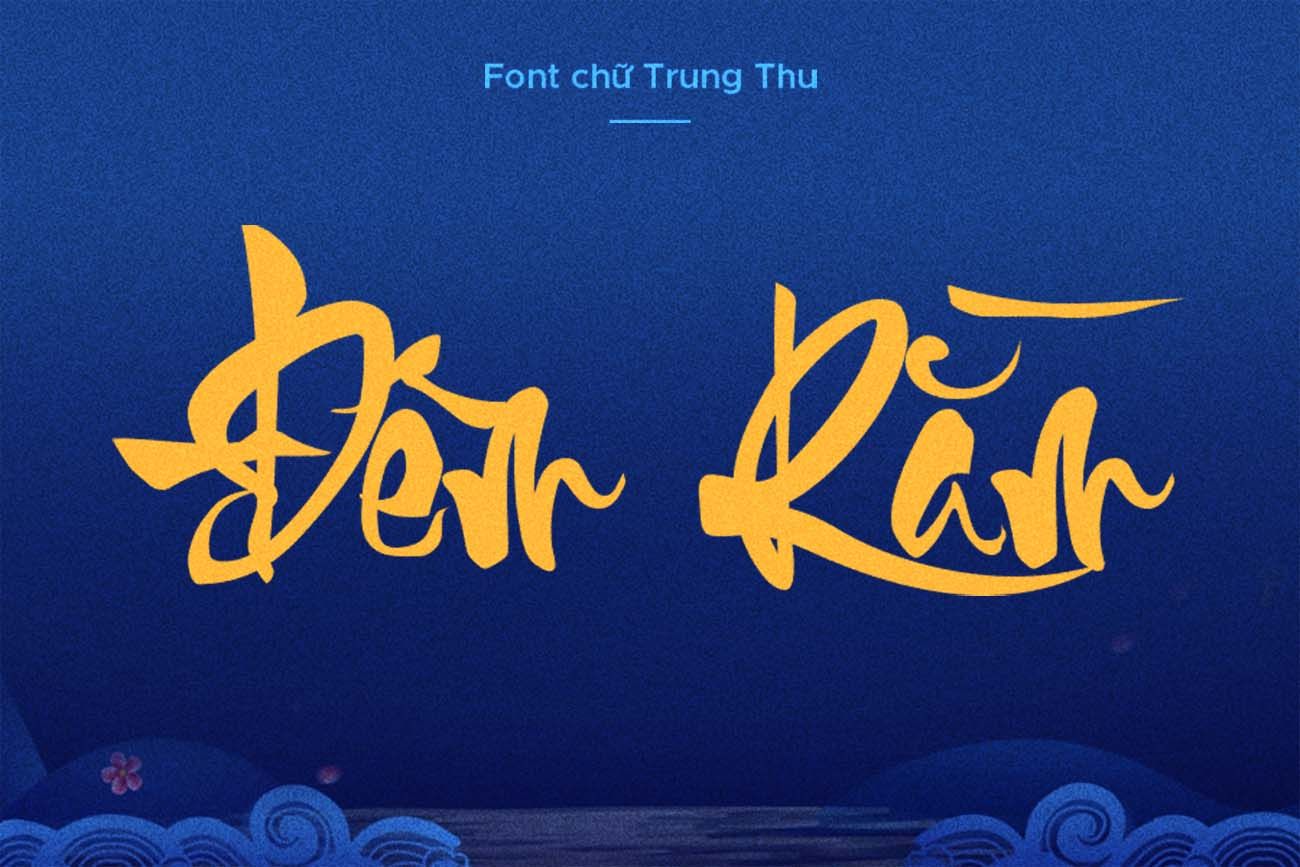
FZ Đại Tự gây ấn tượng với nét bút dày, khoáng đạt. Font này phù hợp cho standee, backdrop sự kiện hoặc bao bì hộp bánh cao cấp. Sự cổ kính và sang trọng của Đại Tự khiến nó nổi bật trong các thiết kế truyền thống.
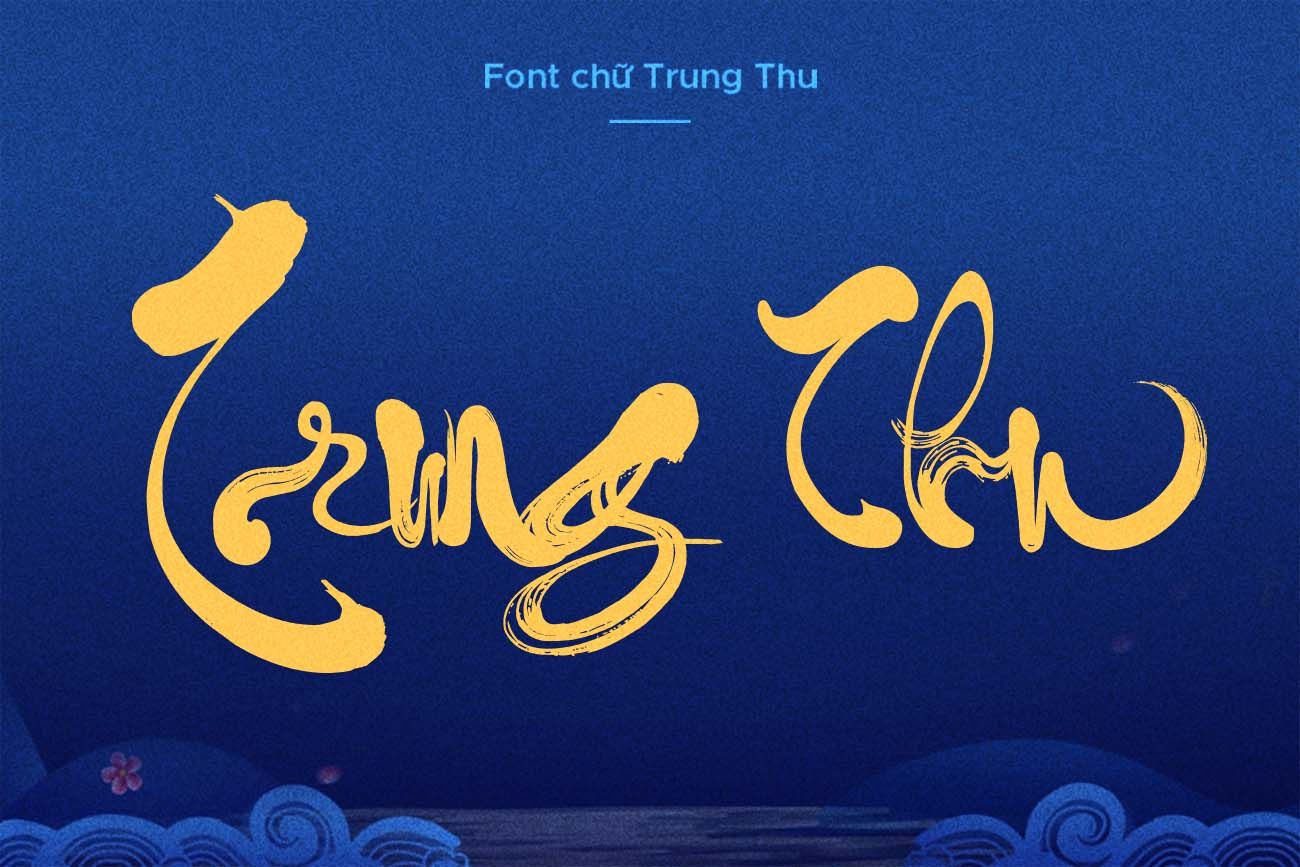
Khác với Đại Tự, FZ Tiểu Tự mang nét chữ nhỏ gọn, mềm mại và gần gũi. Đây là lựa chọn hoàn hảo cho thiệp mời, tờ rơi hoặc những thiết kế cần sự tinh tế và dễ tiếp cận.
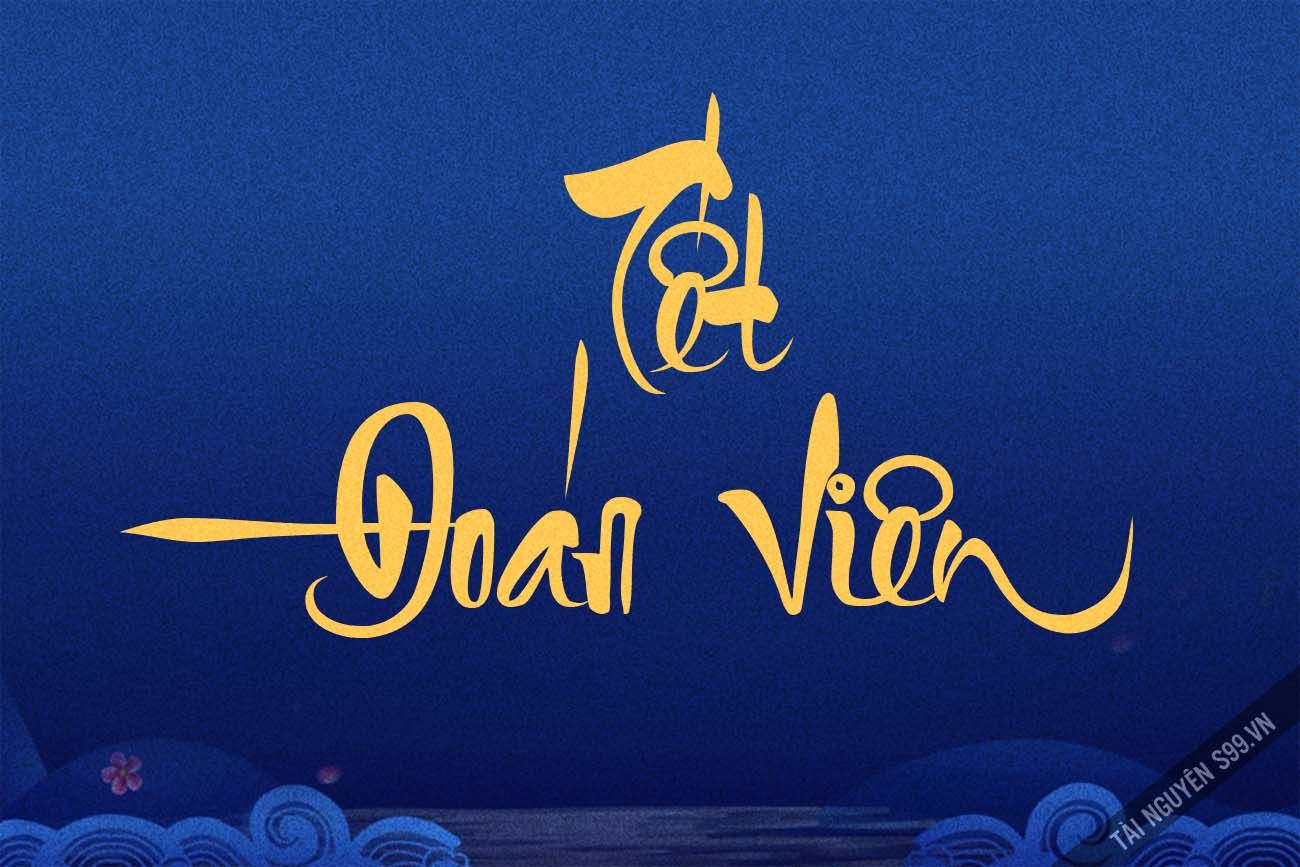
UTM Thiên Ân nổi bật với nét bút mềm nhưng chắc, mang lại cảm giác cổ điển. Đây là font thư pháp Việt hóa miễn phí, dễ ứng dụng trong in ấn và digital. Phù hợp cho poster lễ hội, banner hoặc thiệp chúc mừng.
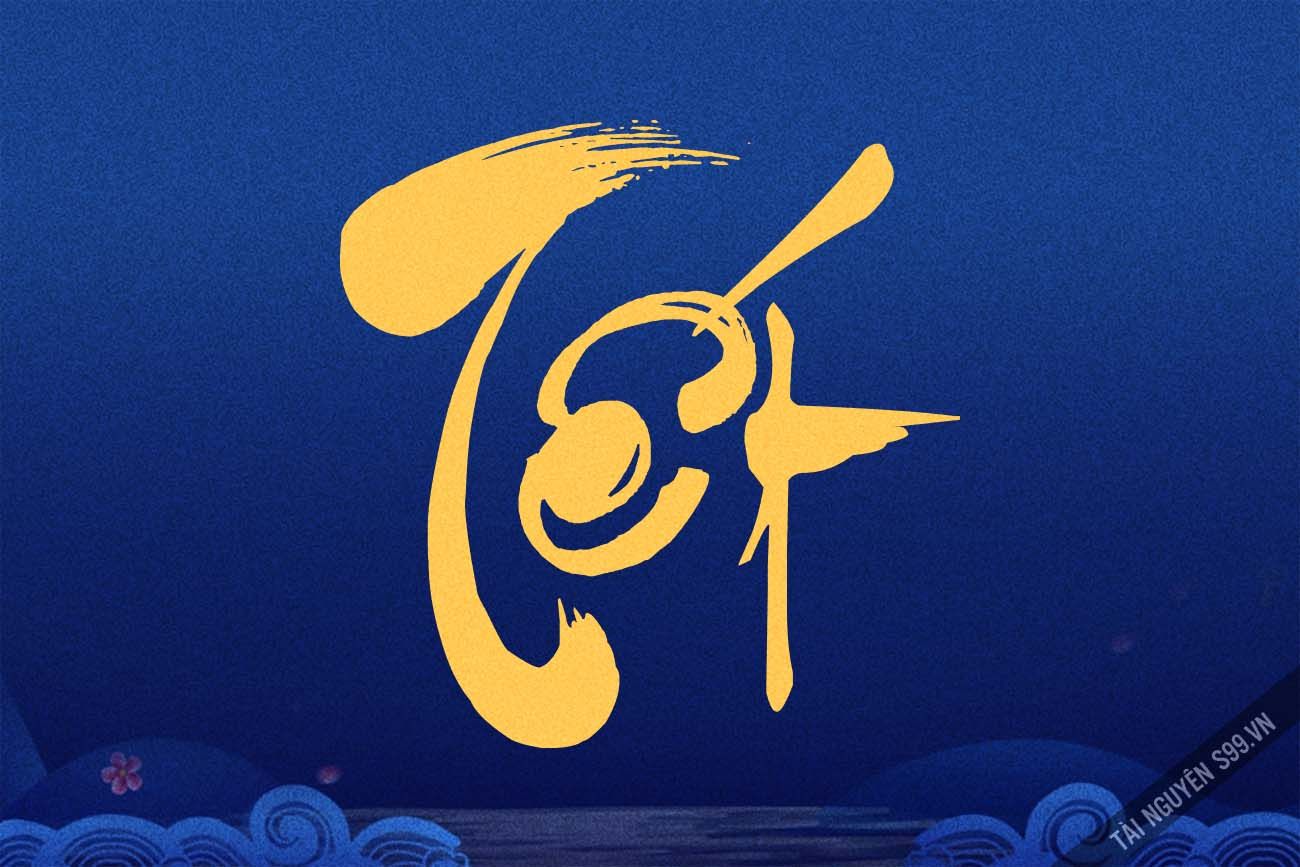
FZ Bút Bi mô phỏng nét bút bi tự nhiên, vừa mang hơi thở hiện đại vừa giữ sự gần gũi. Font phù hợp cho banner, poster hoặc thiết kế kết hợp font sans-serif.
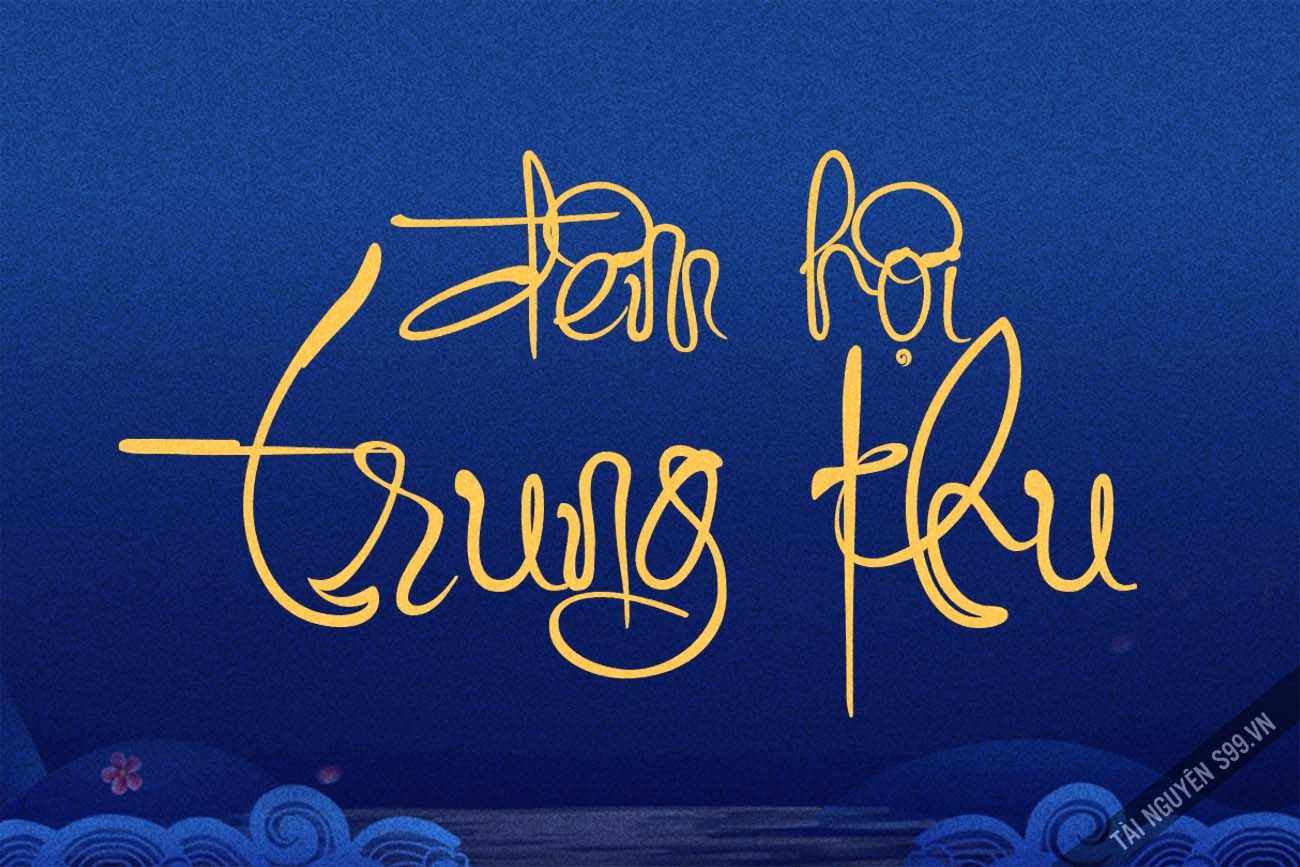
LNTH Peterobscure mang phong cách cổ trang huyền bí, đường nét cách điệu mạnh mẽ. Font phù hợp cho poster sự kiện, bao bì cao cấp và các ấn phẩm nghệ thuật.
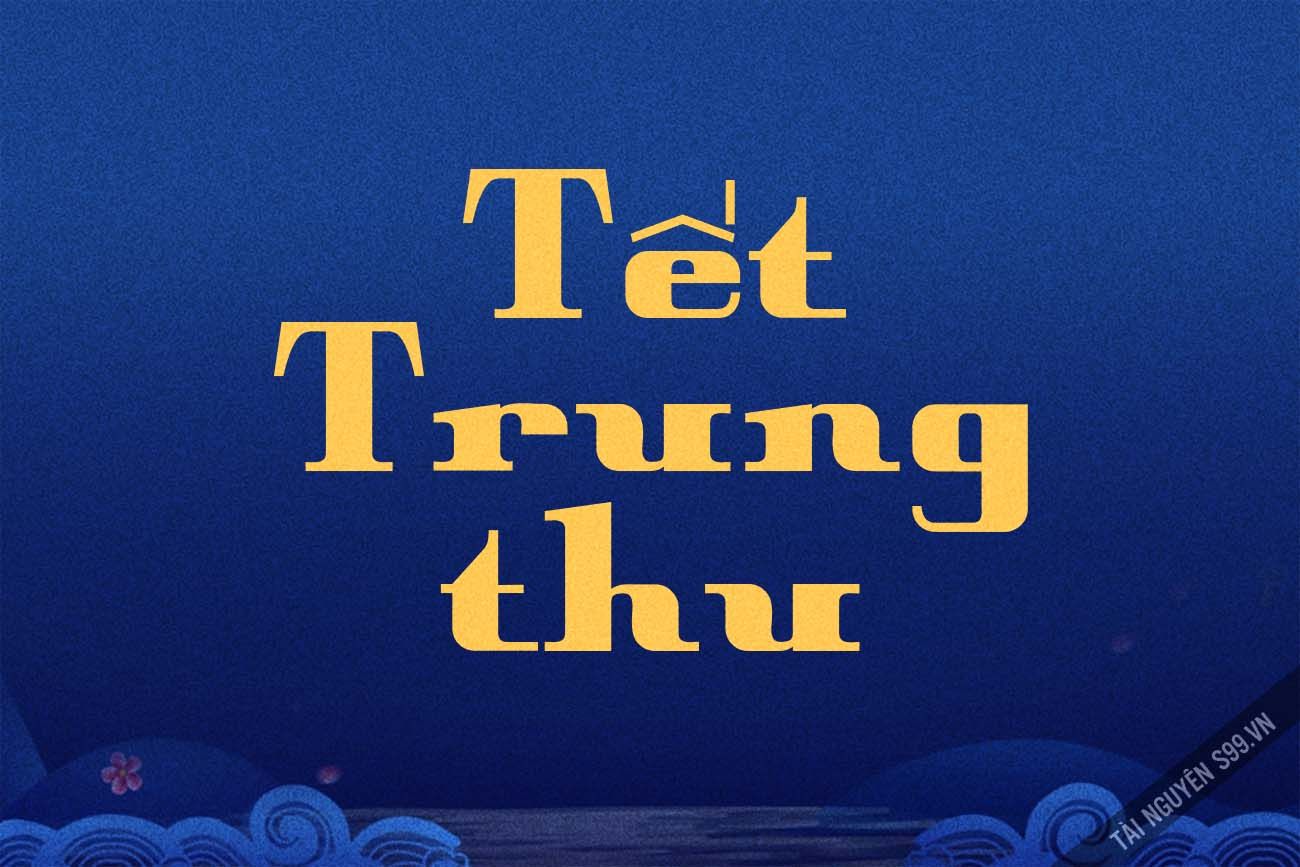
Chinese Prodigy có đường nét chắc khỏe, mang hơi hướng Trung Hoa cổ. Font lý tưởng cho thiết kế bao bì, poster lịch sử hoặc sản phẩm truyền thống.
Tác giả gốc: Attype Studio
Việt hóa: Việt Hóa Team
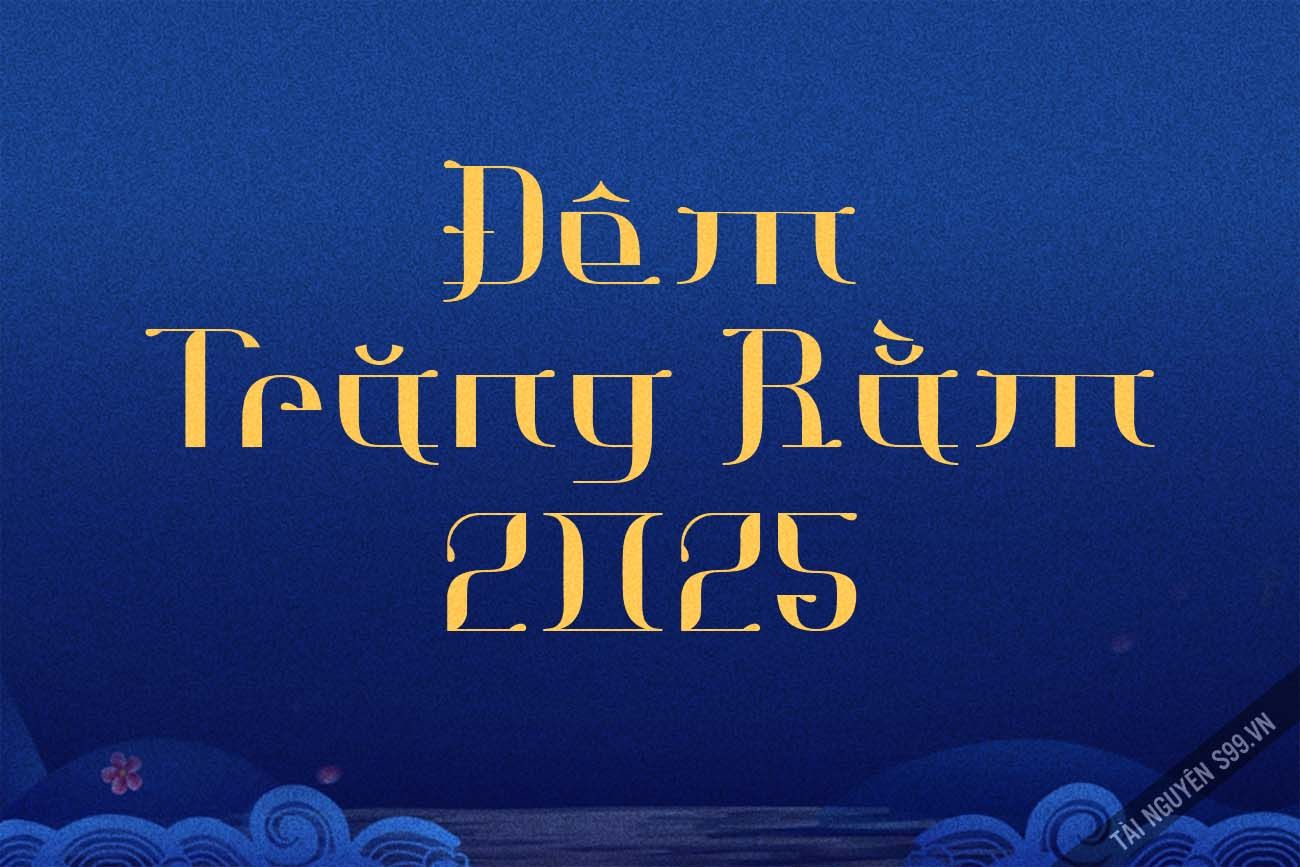
MTD Briliants Typeface kết hợp nét mềm mại và góc cạnh, mang đến cảm giác trang trọng. Font phù hợp cho bao bì hộp bánh, poster lễ hội và thiết kế cao cấp.
Tác giả gốc: Rvq Type Foundry
Việt hóa: MTD Team
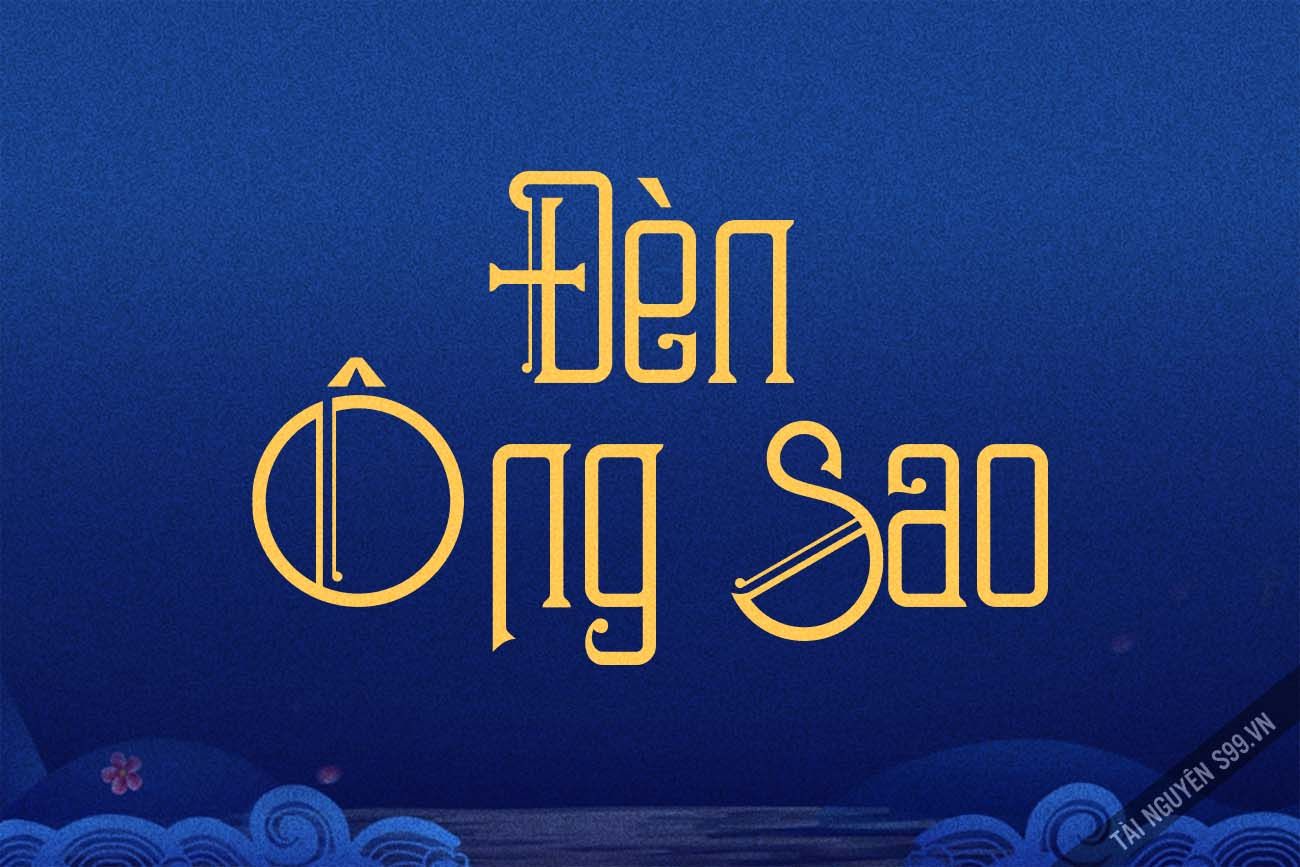
NVN Morning Calm có nét chữ mảnh, thanh thoát, gợi cảm giác nhẹ nhàng và cổ kính. Font thích hợp cho thiệp, tờ rơi và các thiết kế truyền thống.
Tác giả gốc: Kim JinHyuk
Việt hóa: NVN Team
TH Hidayatullah với thiết kế góc cạnh nhưng uyển chuyển, phù hợp cho bìa sách, poster lễ hội hoặc bao bì truyền thống.
Tác giả gốc: Anthonie Van Hayu
Việt hóa: Team TH
SVN Moshimoshi kết hợp hoài cổ và retro Nhật Bản. Font phù hợp cho poster, hộp bánh hoặc branding phong cách cổ điển.
Việt hóa: SVN Team
TH Hoaico 1 mang nét chữ chắc khỏe, gọn gàng, gợi phong cách Tết xưa. Font thích hợp cho banner, thiệp và bao bì truyền thống.
Việt hóa: Team TH
TH Hoaico 2 với các nét tròn đầy, mềm mại, tạo cảm giác ấm áp. Font lý tưởng cho poster, standee và hộp bánh vintage.
Thư pháp cho poster & thiệp.
Retro cho bao bì hoài cổ.
Nghệ thuật/viết tay cho digital marketing.
Không nên lạm dụng quá nhiều font cùng lúc.
Bộ sưu tập 28 Font Chữ Trung Thu & Cổ Trang Việt Hóa 2025 mang đến nhiều lựa chọn từ truyền thống đến hiện đại. Với đầy đủ phong cách – thư pháp, cổ trang, retro, lịch sử, nghệ thuật – đây là tài nguyên không thể thiếu cho mùa lễ hội.